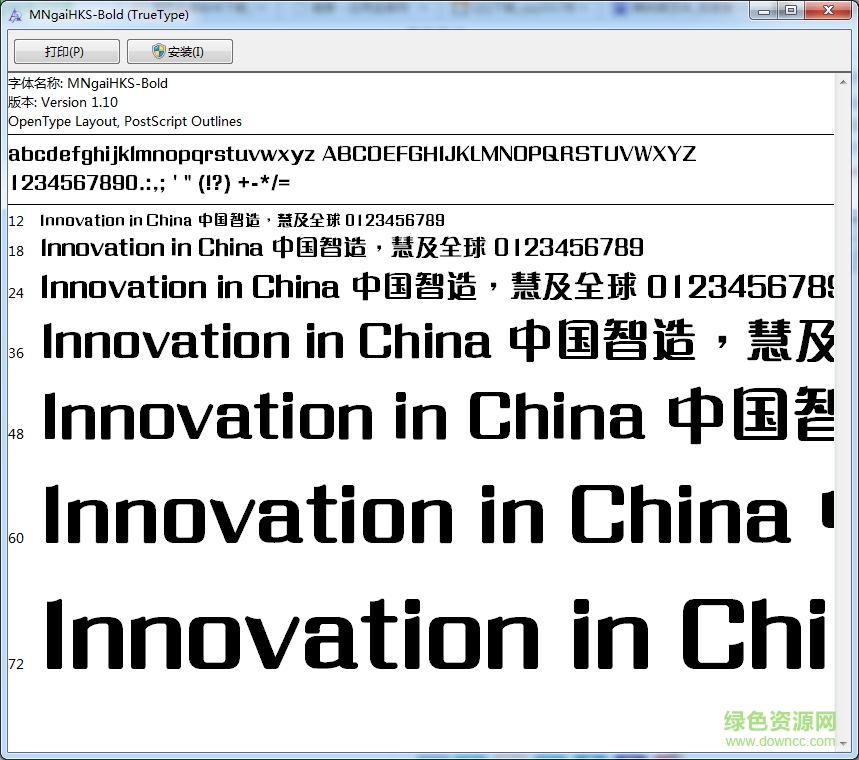
蒙納簡藝字體是一款非常時(shí)尚新潮的電腦字體軟件,字體圓潤可愛風(fēng)格清新,一鍵安裝即可免費(fèi)使用,讓你在設(shè)計(jì)廣告時(shí)所用的廣告詞更加有特色,需要的朋友可別錯(cuò)過了這款經(jīng)典字體,快來綠色資源網(wǎng)下載體驗(yàn)吧!
今天小編為你帶來蒙納簡藝字體。這個(gè)字體顯得格外飽滿,看上去非常有美感,非常適合廣告設(shè)計(jì)、平面設(shè)計(jì)、印刷包裝、正文標(biāo)題等人員使用。